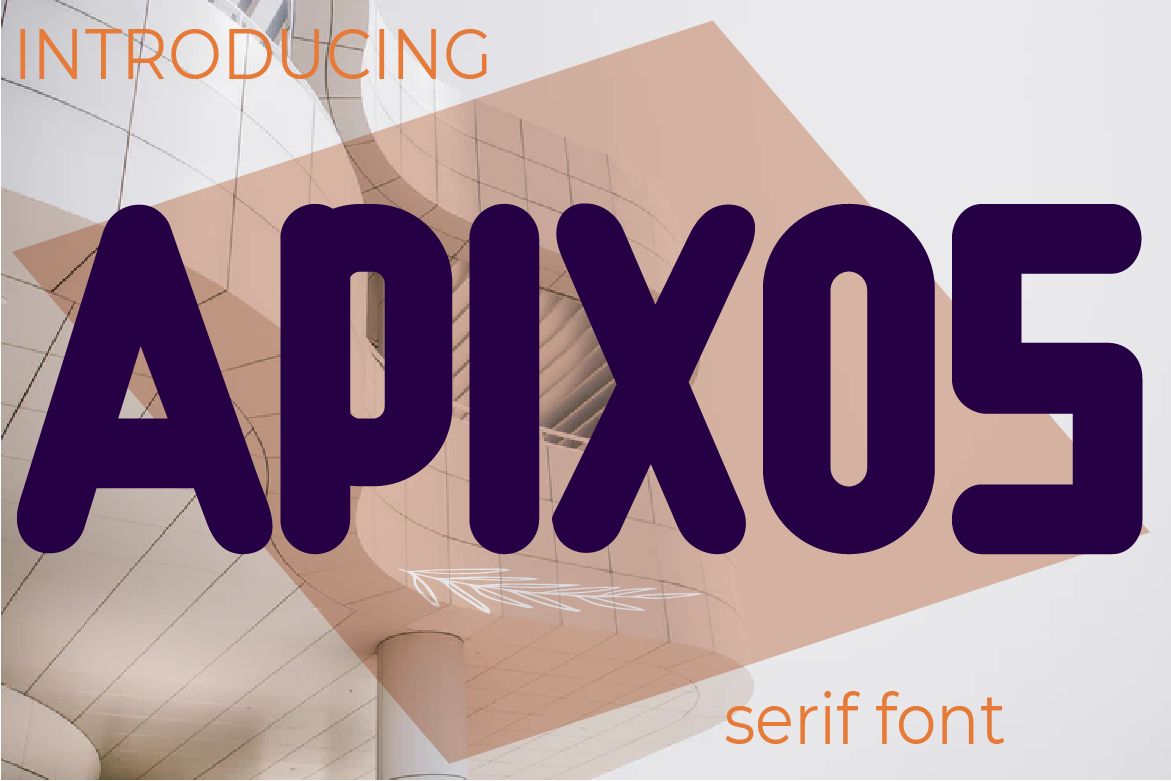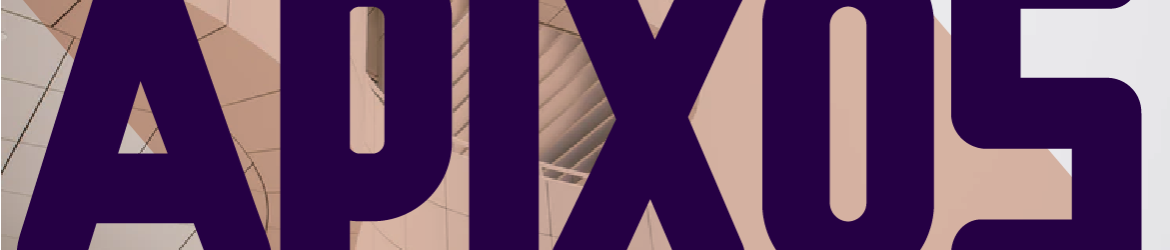
Apixos Font – Download Grátis
A Apixos Font é uma fonte séria que combina elegância moderna com força poderosa. Perfeita para marcas relacionados a mídia e óptica, esta fonte oferece qualidades únicas, tornando-a um recurso valioso para diversas aplicações. Com sua característica marcante e moderna aparência, ela é ideal para designers buscando expressar uma mensagem interessante e memorável, tanto em branding técnico quanto na consultoria inteligente. Seja você um tecnólogo ou consultor dedicado, a Apixos Font está sempre pronta para ajudar você a transmitir sua visão de maneira inovadora no ambiente digital. Seja através da web desenvolvimento, sites e multimídia – esta fonte é versátil o suficiente para atender a qualquer necessidade criativa que você possa ter. Engajante e memorável, a Apixos Font do Designer anumb6 oferece uma combinação única de confiabilidade e inovação no seu campo.